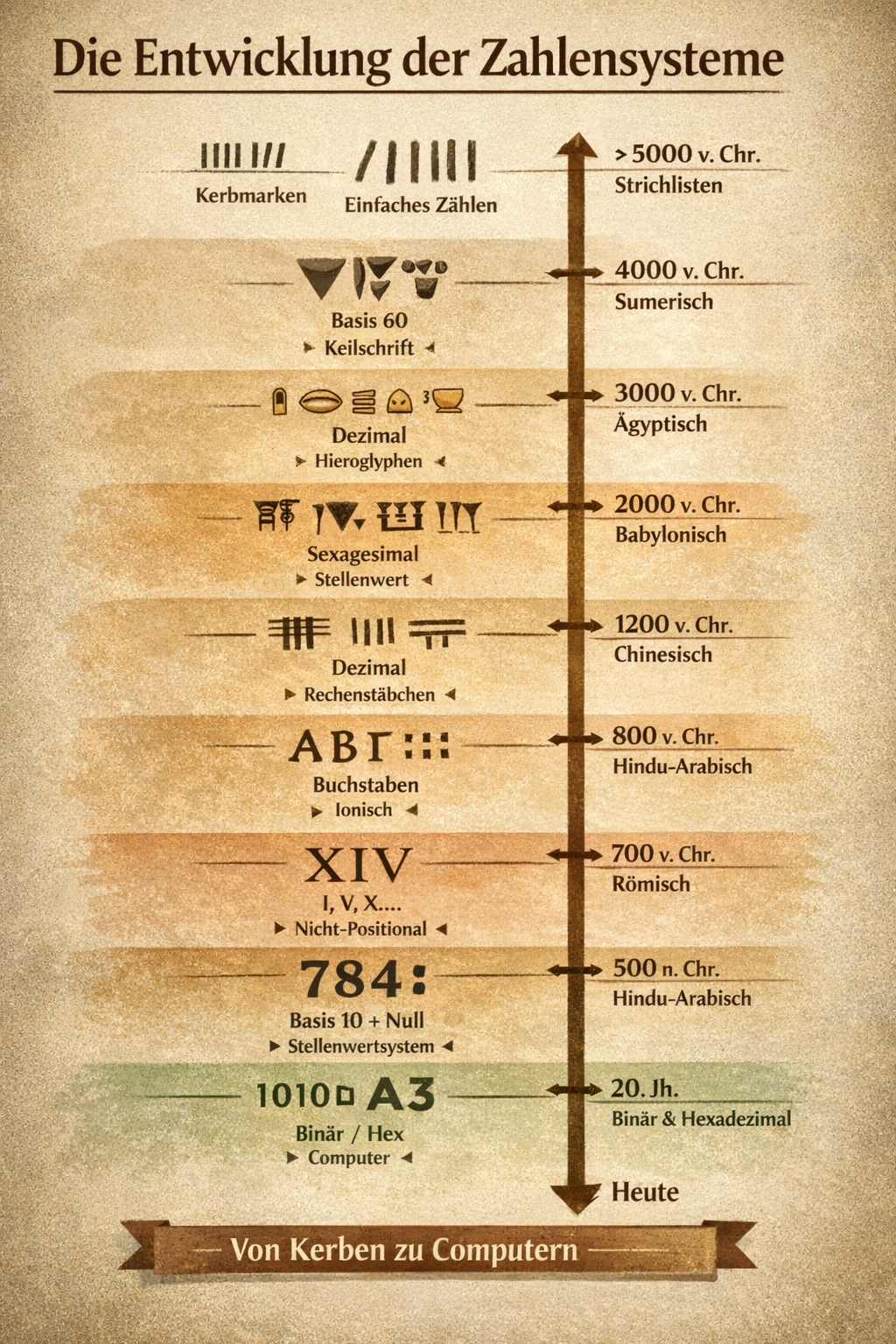
Die ersten Zahlen waren Striche und Kerben in Knochen, später kamen Tonkugeln, Keile und Symbole hinzu. Im alten Indien wurde schließlich die Null erfunden — eine Idee, die über die arabische Welt nach Europa kam und unser modernes Rechnen erst möglich machte.
Zahlen
Auch Zahlen sind Schrift — und sie haben eine eigene, mindestens ebenso lange Geschichte. Von babylonischen Keilen über römische Ziffern bis zu den indisch-arabischen Zahlen, mit denen wir heute rechnen, lässt sich daraus eine eigene Weltgeschichte erzählen.
Zahlensysteme im Vergleich
Wie die Welt zählt